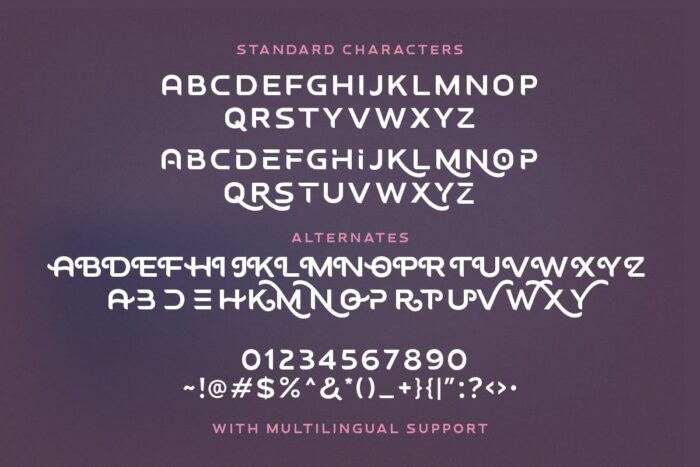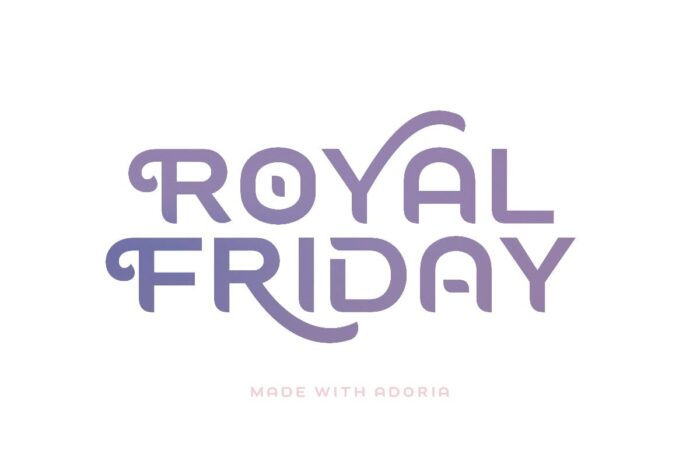
DVN Adora Việt hóa – Font chữ Logo sang trọng và cách tân
Font chữ Adora là một kiểu chữ hiện đại và sáng tạo, lý tưởng cho việc thiết kế logo và các dự án thương hiệu. Với các ký tự được thiết kế mượt mà, font này mang lại cảm giác tinh tế và đẳng cấp. Đặc điểm nổi bật của Adora là sự kết hợp giữa các đường nét tròn trịa và những chi tiết uốn lượn độc đáo, tạo nên một vẻ đẹp vừa mềm mại vừa mạnh mẽ.
Font chữ Adora đi kèm với nhiều ký tự thay thế (alternates), giúp bạn dễ dàng tùy biến logo để phù hợp với phong cách thiết kế mong muốn. Các ký tự này mang đến sự đa dạng và sáng tạo, cho phép người dùng thể hiện cá tính và sự độc đáo trong thiết kế. Với khả năng hỗ trợ đa ngôn ngữ, Adora không chỉ phù hợp cho các dự án trong nước mà còn thích hợp cho các thương hiệu toàn cầu. Đây là lựa chọn hoàn hảo cho những ai tìm kiếm một font chữ đa năng, dễ nhận diện và ấn tượng.